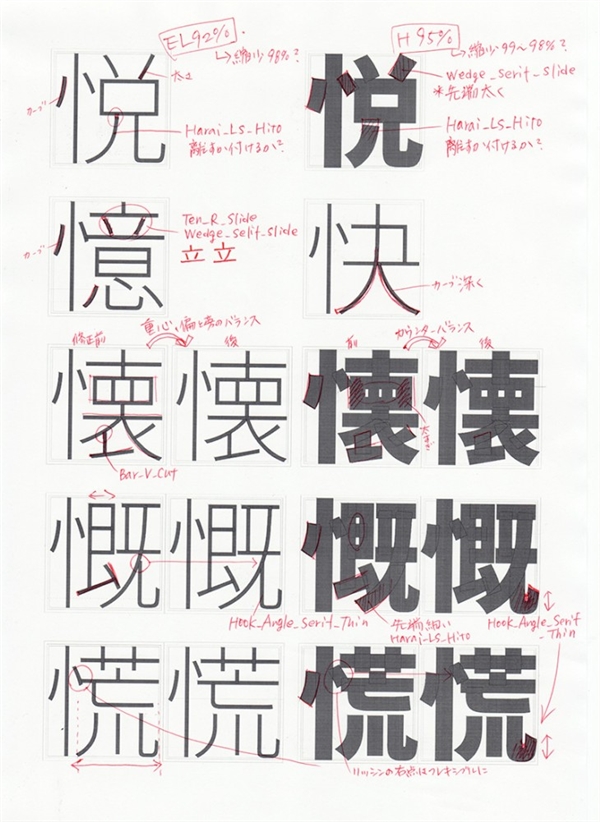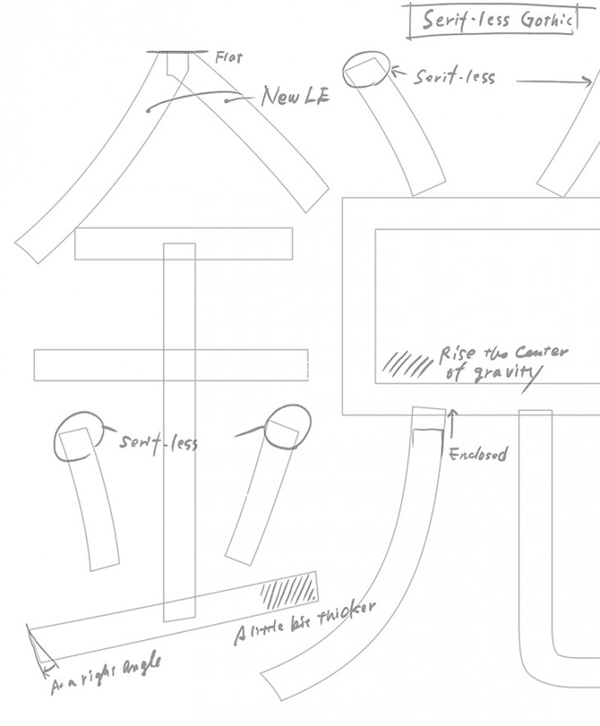
Adobe与谷歌共同发布中/日/韩开源新字体
导语Adobe在线字体库Typekityu与谷歌一起正式发布了新款开源字体:思源黑体(Source Han Sans)
Adobe在线字体库Typekityu与谷歌一起正式发布了新款开源字体:思源黑体(Source Han Sans)。
这款字体由Adobe与谷歌合作开发,风格介于现代和传统之间,提供了对日、韩、中文(简/繁体)的支持,包含了7种不同粗细规格。简体中文方面,它支持中国国家标准GB 18030以及教育部于2013年颁布的《通用规范汉字表》里规定的所有汉字。
虽然由两家公司合作开发,但各自对这款字体的称呼却不一样,Adobe称之为Source Han Sans(思源黑体),而谷歌则称它Noto Sans CJK(CJK:Chinese, Japanese, Korean),并纳入了Noto pan-Unicode字体家族。
这款字体的开发持续了4年之久,在双方的合作中,谷歌参与了对项目方向及字体特征的定义,影响了字体设计,对字体的设计及文件提供了本地测试,并提供了资金支持。而Adobe则在字体设计和开发方面展现了强大的实力,带来了坚实的字体设计经验、大量协作和自动化技术。
除了Adobe与谷歌,还有多家亚洲顶级字体设计公司参与制作,包括常州Sinotype、Iwata和Sandoll。他们设计和绘画了大量的字形。
Adobe做开源字体,可以利用它优化自家的设计软件,而谷歌则会把这款字体用于自家相关产品的开发。